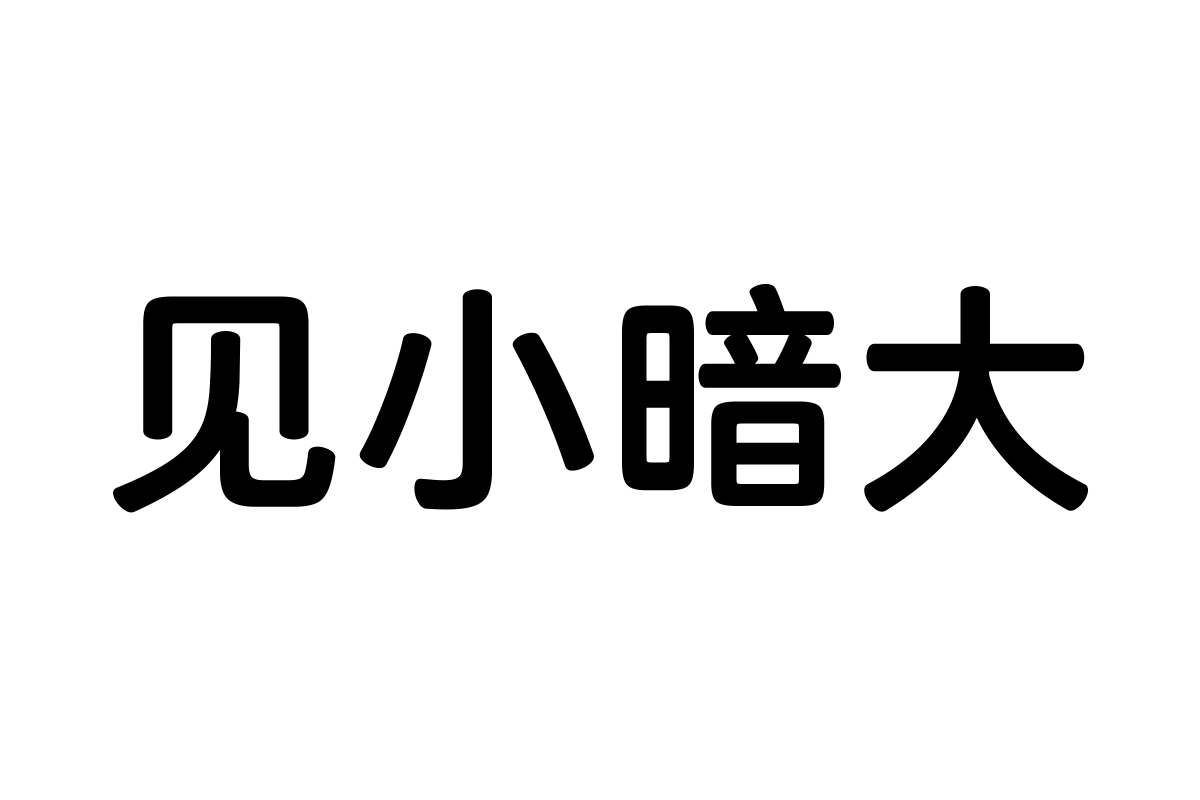
汉仪正圆-75是一款现代简约风格的中文字体,适用于各种商业、广告和设计项目。它具有清晰易读的特点,适合用于标题、正文、广告牌等需要突出显示文字的场合。该字体由汉仪公司设计,具有多种字重选择,包括常规字重和特殊字重,以满足不同设计需求。此外,汉仪正圆-75还具有较好的可读性和易识别性,适合在各种媒体上使用。